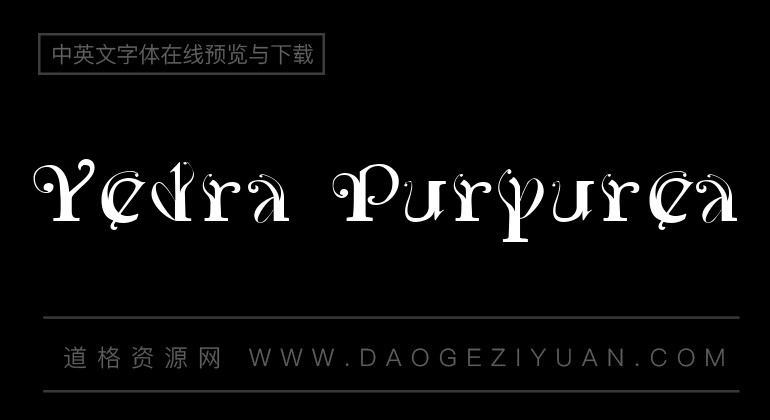
Yedra Purpurea 是一种美丽的手写风格字体。这个字体设计灵感来自于西班牙南部的一个小城镇,因为该城镇有很多覆盆子植物,因此设计师决定将字体命名为 Yedra Purpurea,意为“紫色的覆盆子”。 这种字体非常适合用于手写信件、贺卡、海报和其他各种印刷品上。它的线条流畅、优美,每个字母都带有一些自然的笔画变化,因此它看起来非常有机、自然。除此之外,该字体还包括许多装饰性笔画和字符,可以帮助您创建出更加独特的设计。 总的来说,Yedra Purpurea 是一种非常漂亮、优美的字体,适合用于各种印刷品的设计中,能够为您的设计增添一份个性和艺术感。内容介绍
Yedra Purpurea是一款非常不错的手写艺术字体,具有很好的视觉感,适合于文化类的宣传设计、商业类品牌的广告和产品包装设计以及个性化文字排版等较多场景。